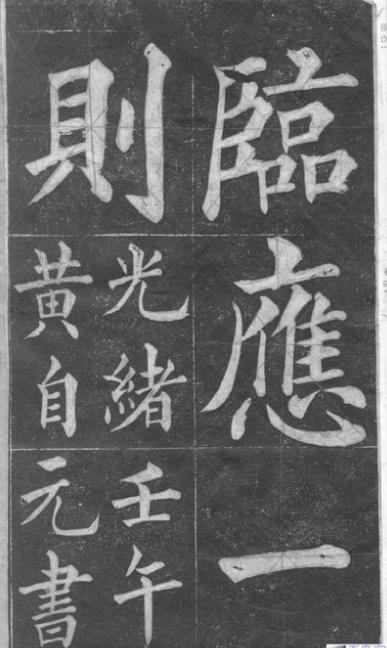
黄自元
黄自元简介
简介  黄自元(1837--1918),字敬舆,号澹叟,湖南安化县龙塘乡人,清末书法家,实业家。生于道光十七年(1837),清同治六年(1867)举于乡,次年殿试列第二(榜眼),授翰林院编修。曾任顺天乡试同考官和江南乡试副考官。郑沅于《敬舆公七十寿序》中曾说:“典试江南,被议镌级。或云可以入资捐复,而卒不为。终被朝廷昭雪,起用检讨。”
光绪年间,黄历任河南道、陕西道监察御史,简放甘肃宁夏知府。在任期间,常跨马出巡,考察河工,征求民隐;进而精修暗洞,以泄黄河之卤,宁夏人至今利之。至中年,因丁忧回籍,不复出仕。
中日甲午战争爆发后,清廷起用湘军。黄被调北上,兵败后,只身自海上逃归。此后定居长沙,先后主讲湘水校经堂及成得书院,与诸生析疑释难,勤诲不倦。民国7年(1918)病逝。
黄善书法,著有《间架结构九十二法》(已收入《中国书法大辞典》)。后经湖南美术出版社重印和出版的,尚有《黄自元临九成宫》和《间架结构九十二法》。
生平
生于道光十七年(1837)。
同治六年(1867)举人,1868年(同治七年)中进士第二名,授翰林院编修。九年任顺天乡试同考官。十二年任江南乡试副主考。以事被议削级,旋授翰林院检讨。历充顺天乡试同考官、江南乡试副考官,迁河南道监察御史,宁厦府知府。一生勤于书法,博采颜、柳、欧各家之长,自成“黄”体。曾为同治帝生母录写神道碑,被誉为“字圣”。所书柳公权《玄秘塔贴》、欧阳询《九成宫贴》、由长沙墨香蓉书画店刻板印售,开长沙书写刻印字贴之先河。卒于长沙。